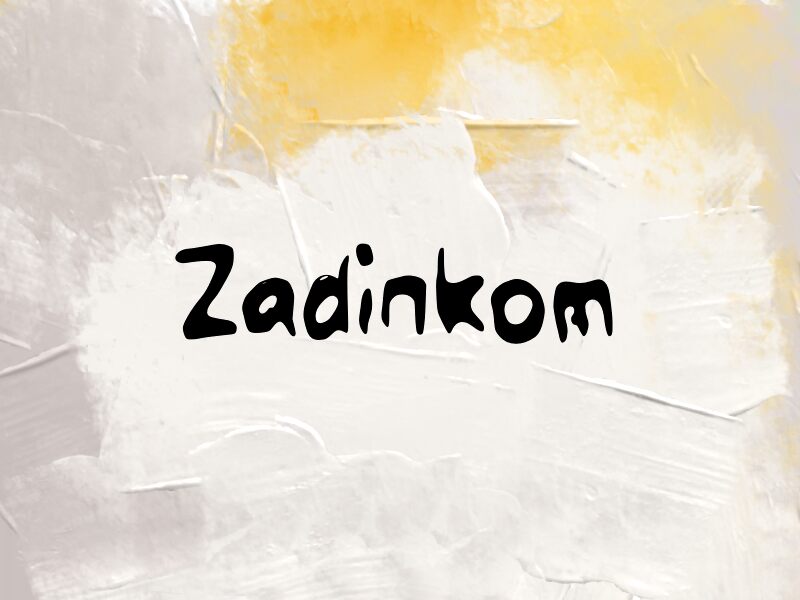
Zadinkom, une police pinceau gratuite créée par Wep, capture le mouvement décontracté et peint à la main des coups de pinceau rapides. Ses lettres sont douces et légèrement arrondies, avec des courbes irrégulières et un rythme spontané qui donnent au texte une allure vivante, loin de la rigueur habituelle.
C'est un choix tout naturel pour des titres d'affiches, une identité de café, des emballages, des couvertures ou des visuels réseaux sociaux où l'on recherche une touche humaine et authentique plutôt qu'une finition parfaite. Elle convient également parfaitement aux titres courts et aux logos, car ses formes larges et expressives font leur effet, même en peu de lettres.